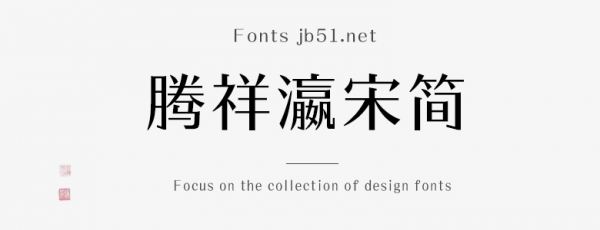
騰祥瀛宋簡(jiǎn)-W4是一款不錯(cuò)的藝術(shù)字體,由騰祥字庫(kù)出品,這款字體字字精美、結(jié)構(gòu)端正、重心平穩(wěn)、美觀實(shí)用,適合應(yīng)用于藝術(shù)設(shè)計(jì)、平面宣傳設(shè)計(jì)、網(wǎng)頁(yè)設(shè)計(jì),書法字帖等領(lǐng)域,需要的朋友可以前來(lái)本站下載。
此款字為騰祥瀛宋系列字庫(kù),是騰祥公司自主精心設(shè)計(jì)開發(fā)的精品正文字庫(kù)。一共10款粗細(xì),以期滿足用戶不同領(lǐng)域的用字需求。此款字為瀛宋W4,可用于正文、小標(biāo)題等。整個(gè)系列字庫(kù)風(fēng)格完全一致,不管是常用字或是非常用字,字字精美、結(jié)構(gòu)端正、重心平穩(wěn)、美觀實(shí)用。此款字為騰祥公司推送《2019森澤字體大賽》參賽作品。